BentoML — софт, с помощью которого можно писать приложения со встроенным искусственным интеллектом. В библиотеке Bento есть набор моделей, уже обученных на разных видах данных, но каждый разработчик может загрузить свою. С помощью Bento уже были написаны, например, голосовой помощник, редактор изображений и программа, которая помогает анализировать рентгеновские снимки.
В заголовках на сайте проекта — Replica из коллекции Lineto, а в подзаголовках и наборе — Atlas Grotesk Commercial Type.
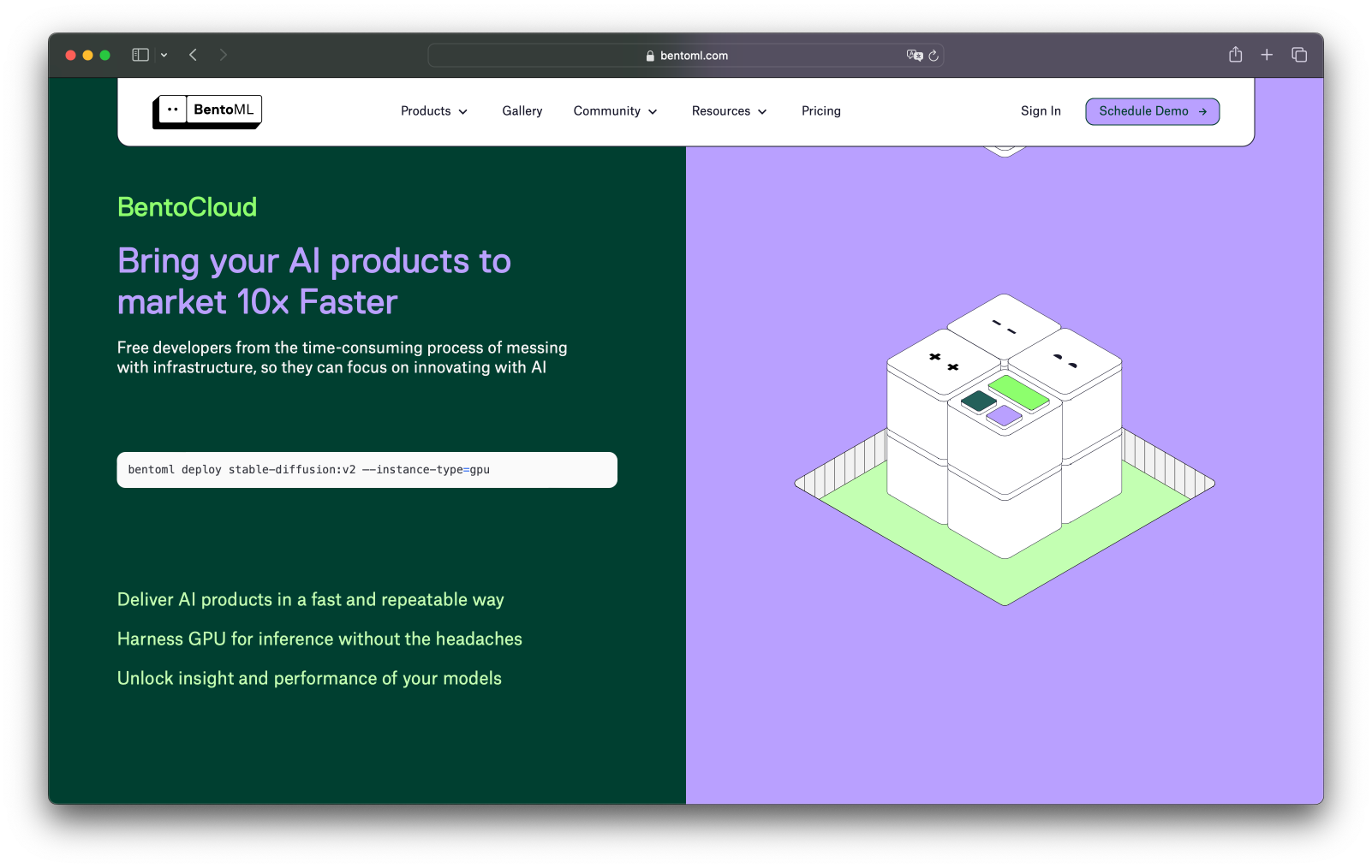
Atlas Grotesk был сделан на заказ для Munich Re, одного из мировых лидеров на рынке перестрахования. Шрифт намеренно игнорирует последние тренды корпоративной типографики и обращается к чёткой и оптимистичной эстетике нидерландского модернизма. В коллекцию Atlas также входит моноширинный